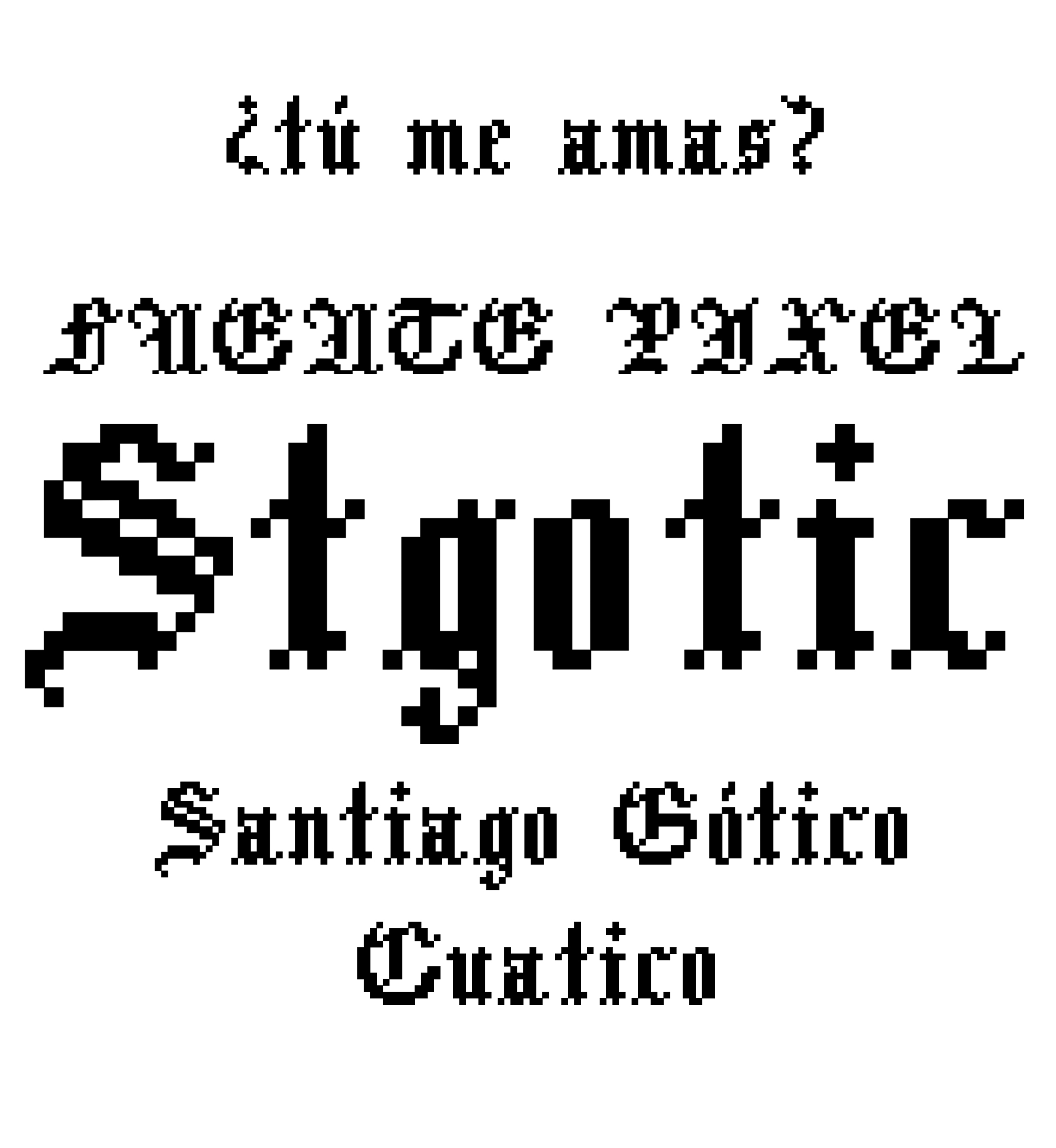
Stgotic
| Año | 2006 — Actualizada: ( 2012 ) |
| Créditos | Daniel Hernández |
| Descripción | Stgotic, diseñada en 2006, fue la primera fuente digital diseñada por Daniel Hernández. Es un tipo de letra negra diseñado para dispositivos de pantalla de baja resolución. Stgotic se diseñó para verse a 8 pts (y múltiplos de 8). |